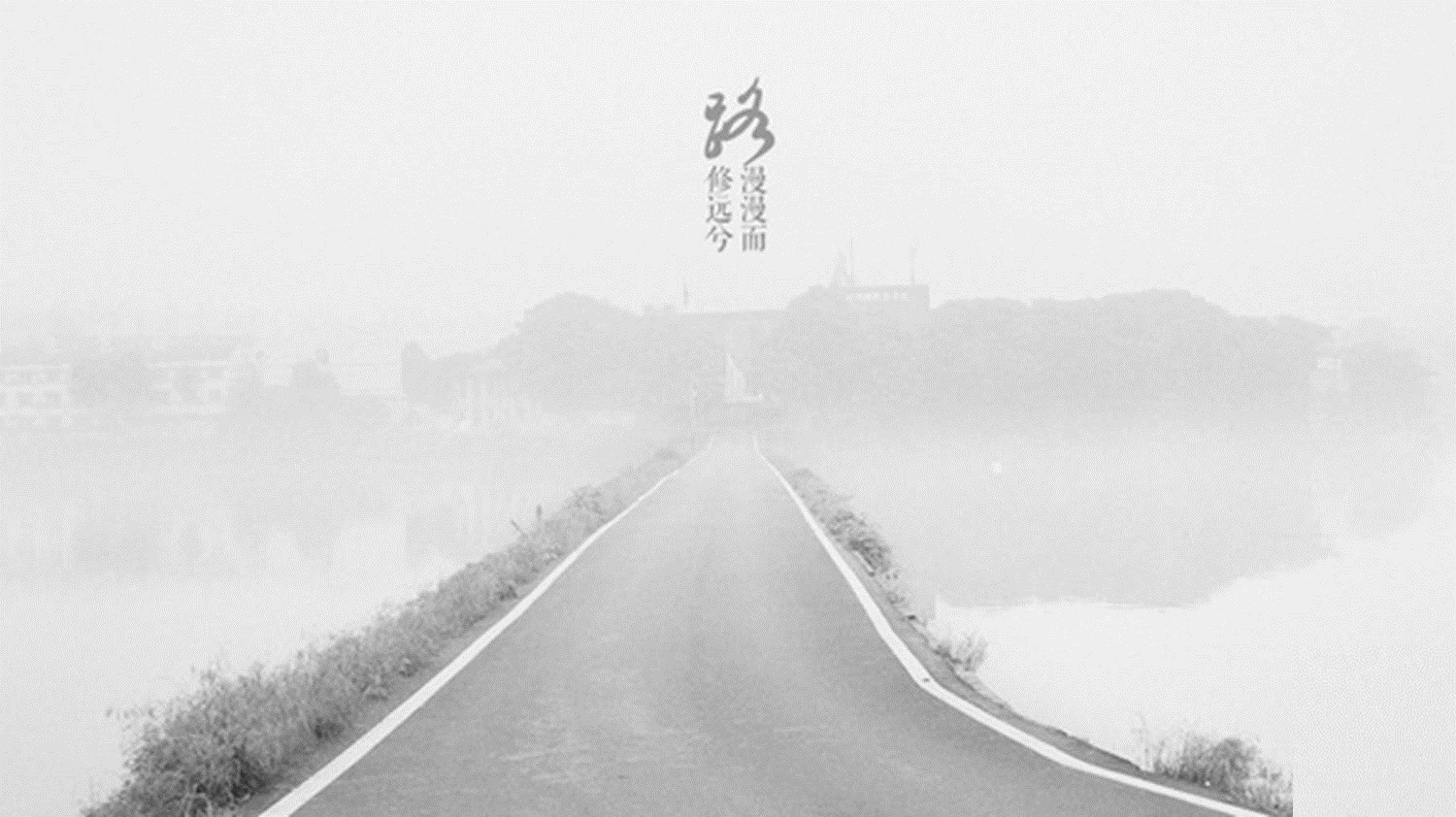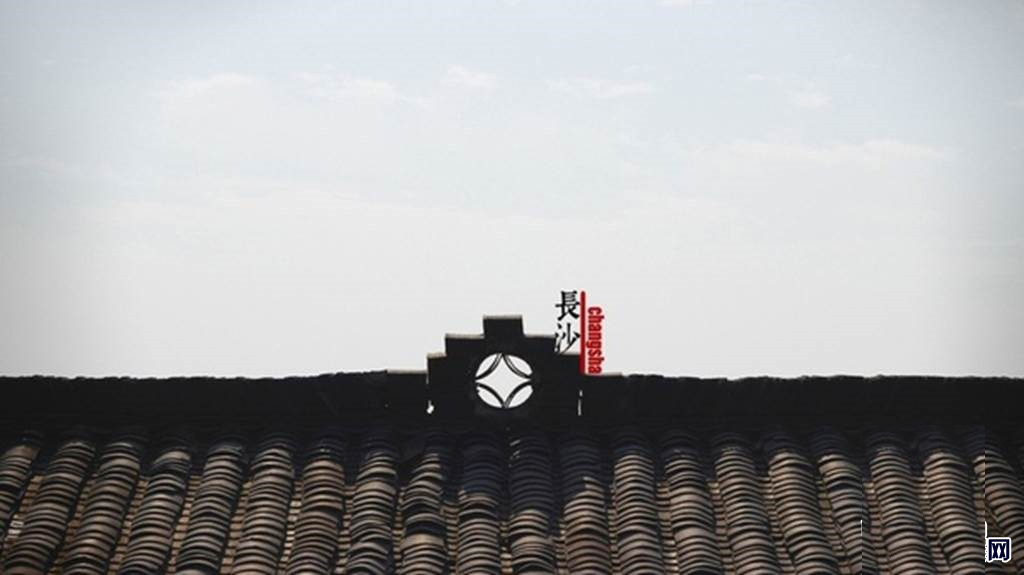
图文搭配是是平面设计的基本功。给照片配上文字,与平面排版有相通之处,但因为偏重不一样,所以处理方式截然不同。照片的文字,重在衬托照片,而平面设计的文字则重在传达力量。前者更多的是一种点缀,而后者更多的是一种武器。所以,照片的文字是为了引导人们更好的观看照片,而不是喧宾夺主。这篇我着重描述具象,当然也会体现出精神。希望大家认真阅读,学习图文搭配的方法。
给照片配上文字,与平面排版有相通之处,但又截然不同,照片的文字,重在衬托照片,而平面设计的文字则重在传达力量,前者更多的是一种点缀,而后者更多的是一种武器,所以,照片的文字是为了引导人们更好的观看照片,而不是喧宾夺主。
上面这点至关重要,因为一不小心,你就可能走火入魔,把你的照片变成了平面设计作品。
举个很简单的例子,以这幅照片为例:
虽然这幅照片的文字很吸引人的眼球,但这个文字是平和的,没有攻击性的,它重在描述事实,起的是辅助性的作用,哪怕它的位置很显眼,但人们分配给它的注意力却是有限的,这就是属于给照片配字而不是平面设计。
当然,有时候二者的界限并不是十分的明显,比如:
这幅作品的文字是平和的,不具有攻击性的,但它又是经过精心设计的,从花纹到字体都是经过雕琢的,因此,你很难判断它的性质。不过在正规的摄影比赛中,一般都不允许添加修饰性的文字,原因之一就是因为修饰性的文字会让图片形成一种设计感,进而影响人们对图片本身的判断,比如这幅图,去掉文字你会感觉是非常普通的摄影作品,但加上文字之后你会感觉还比较不错。
一般而言,采用平和的描述可以很大限度的避免你的摄影作品变成平面设计作品。
我归纳了一下我常用的添加文字的方法:
文字渲染型朴实无华型底纹型文字线型字体搭配型颜色搭配型大小组合型图文混合型印章型镂空型
一:文字渲染型
何为文字渲染型?简单点儿讲,就是让人们分配更多的注意力到文字,进而用文字优化画面。咦?这不是有点儿步入误区了吗?不是不要让文字吸引过多的注意力吗?咳咳,这是个例外。
运用这个类型,最重要的就是要选好字体,手写体?粗犷体?纤细体?字体的选择几乎决定了你的最终效果。
比如这幅作品:
因为文字占据的空间大,所以人们很容易就被它吸引到,又因为文字极具煽动性,所以会让人们的注意力停留的时间更长,而在字体的选择上,选择了更加坚硬的字体来配合画面,加上黑色文字的选择,与整体画面的融合十分到位。
二:朴实无华型
这种类型十分常见,也运用得非常广泛。简而言之,这种类型就是纯文字,并且没有颜色的对比,大小的对比,字体的对比等。
这种类型又有两个基本型:竖直型和水平型。
比如:
这就是竖直型。
再比如:
这就是水平型。
这种类型的关键在于:把握好字体的选择,间距的选择和文字的选择。
字体要融合画面,间距根据需要增减,文字一定不能与画面格格不入。具体我就不展开了,因为这也不是三言两语就可以讲清楚的事情。
三:底纹型
什么叫底纹型?就是在文字区域存在一个底纹将文字与画面分离开来。
这种类型的优点就是能够最大限度的降低画面对文字的影响,让你拥有更大的空间选择文字与排版,并且能更加有效的凸出文字。
我们经常会遇到这样的情况,当我们在画面输入文字的时候,因为颜色差异不大的关系,文字经常被画面掩盖掉了,这时候,底纹型就可以一劳永逸的解决这个问题。
当然,这种类型也有一个明显的缺点,就是如果安排不好,就像是在画面上打了一个补丁一样。
比如:
下面这幅图,因为整体色调偏暗,如果再加上黑色文字,会出现文字看不清的状况,而运用底纹型可以有效解决这个问题。
底纹型的关键在于如何让底纹更好的融合进画面而不显突兀,主要的方法有一:让底纹本身具有设计感。二:调整不透明度。三:将部分文字置于底纹之外以加强底纹与画面的联系。
四:文字线型
所谓文字线型,就是在画面的文字之中有一根线,这根线呢,通常有三种表现形式:水平,垂直和斜线,而线本身又有两种形式:实线和虚线。
不要小看这根线,它可以发挥很大的作用,主要体现在平衡画面,凸显层次,引导观者等。
比如:
再比如:
这种类型的关键在于安排好主次关系,选择好线条和选择好摆放的位置。
五:字体搭配型
这种类型没有太多要讲的,主要就是不同字体类型进行搭配,同中求异,凸出重点,个人建议字体不要太多,2-3种足矣,另外建议印刷体和手写体进行搭配。字体搭配还包括:中英文搭配,文字与数字搭配等。
六:颜色搭配型
这个也很简单,就不展开了,注意的要点是:颜色不要太多,2-3种即可,色彩的纯度不要太高,不然容易非主流。
七:大小组合型
这个很简单了,前面也已经用到过了,就是让字体有一个大小的变化,进而突出重点和拥有节奏上的变化。
当然还有很多种组合方式,比如这种:
上面这三种类型其实经常是综合使用的。
八:图文混合型
这种就是在文字中还镶嵌着图片,图片一般以个性签名,图腾,特殊符号等构成,可以很好的活跃画面。
九:印章型
这个类型的适用范围稍微狭窄一些,主要是运用在中国风的照片里面。
十:镂空型
所谓镂空型,就是文字是镂空的。对于镂空型的,需要注意的是底色的选择和字体的选择,一把而言,白色底色就不错,如果你能选到更适合的当然更好,字体的话要够宽大,不然太纤细就完全没有效果了。